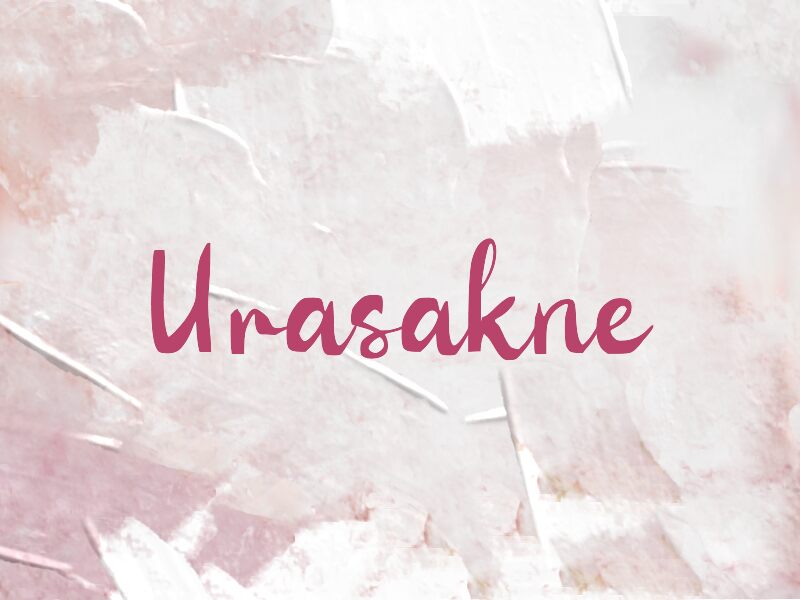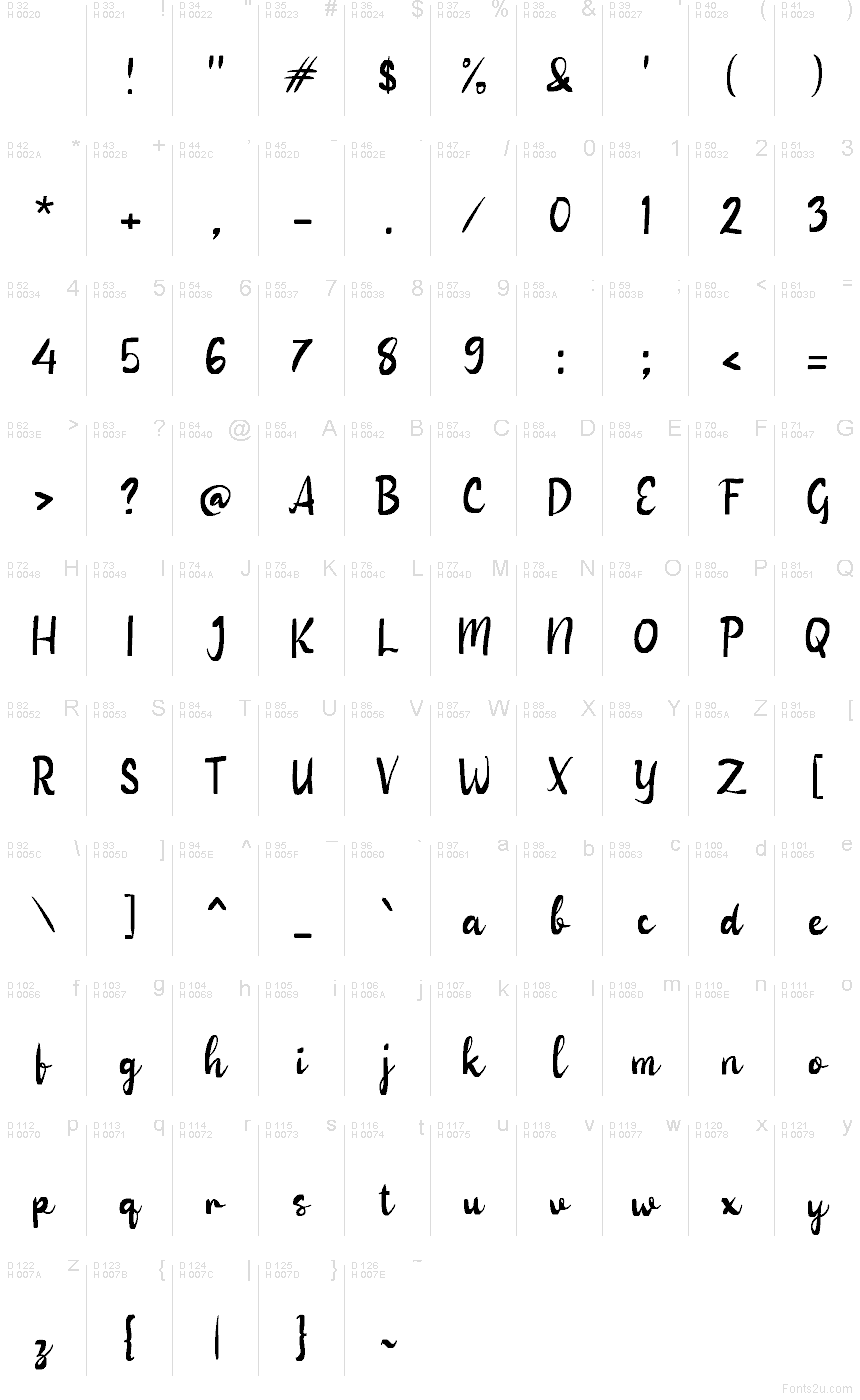
Urasakne от wep — это бесплатный шрифт в стиле brush script с быстрым, «ручным» почерком и непринужденным уличным характером. Буквы выглядят так, будто написаны одним движением: высокие штрихи, округлые соединения и выразительные кончики кисти задают свободный, живой ритм, лишенный излишней прилизанности.
Шрифт идеально подходит для заголовков на плакатах, брендинга кофеен, обложек музыкальных релизов, упаковки и оформления соцсетей, где нужно добавить рукописный акцент, избежав приторности. Поскольку штрихи остаются широкими и слегка неровными, Urasakne также отлично смотрится в коротких текстах, эскизах логотипов и крупных цитатах, где важнее движение, а не строгая формальность.
Urasakne
Презентация и наглядный образец шрифта Urasakne